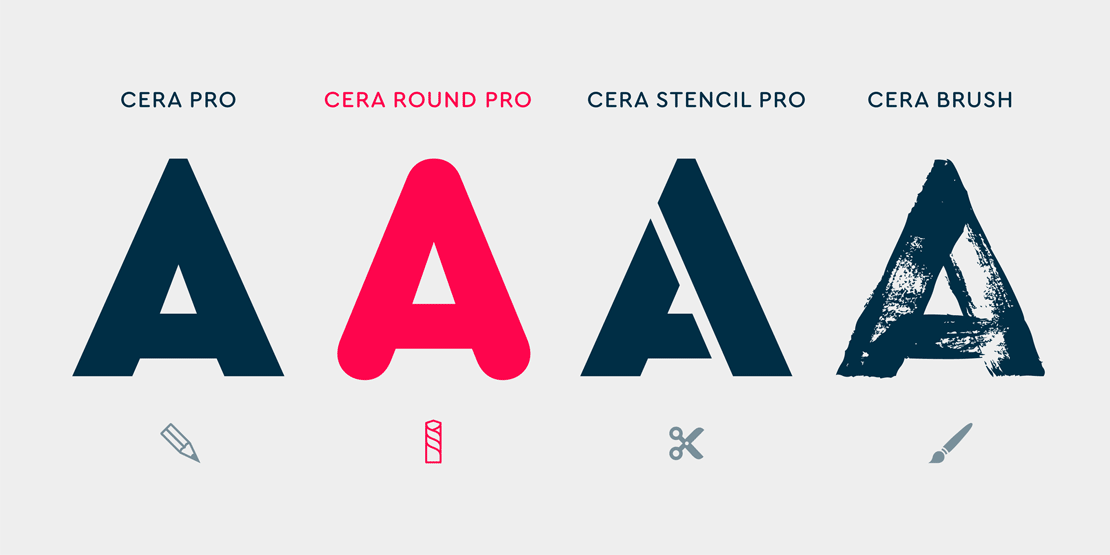
Runde »Cera«
Die TypeMates aus Hamburg stellen die neue »Cera Round Pro« vor. Die Schriftfamilie komplettiert die bisher erschienene »Cera Collection« um Fonts mit kreisrunden Strichenden.
Die paneuropäische »Cera Round Pro« ist die abgerundete Variante der »Cera Collection« mit dem Bestseller »Cera Pro«, der eleganten »Cera Stencil« und der handgemachten »Cera Brush«. Die Schriftfamilie bietet ein breites Spektrum – von technisch und mechanisch bis hin zu weich und freundlich. Sie soll sich somit für Branding, Editorial Design und Interface-Design gleichermaßen eignen.
Bei der Entwicklung haben sich Lisa Fischbach und Jakob Runge nicht einfach auf das Abrunden der Buchstaben beschränkt. Etliche Glyphen wurden neu gezeichnet, um dem neuen, runden, geometrischen Charakter zu entsprechen und die Lesbarkeit in ihren abgerundeten Ausprägungen zu erhalten. Außerdem wurden typografische Extras wie Tabellenziffern, automatische Brüche oder nützliche Symbole und Dingbats ergänzt.
Neben lateinischen Sprachen unterstützt Cera Round auch griechische und kyrillische Zeichensätze mit lokalisierten Alternativformen. Wie die Schrift entstanden ist, erfährt man in einem Making of.